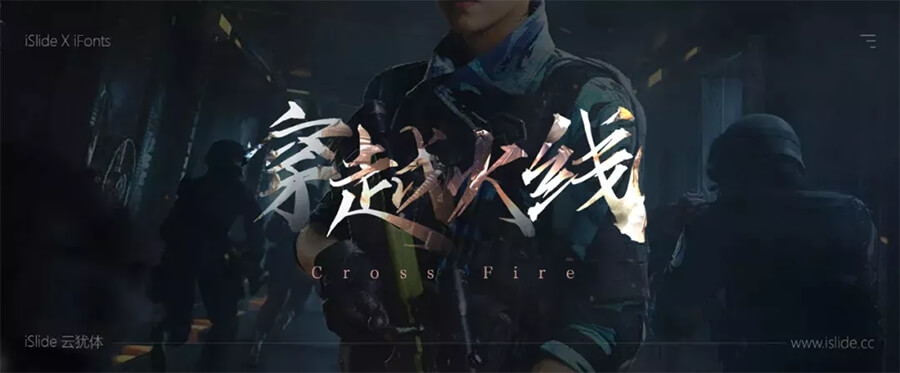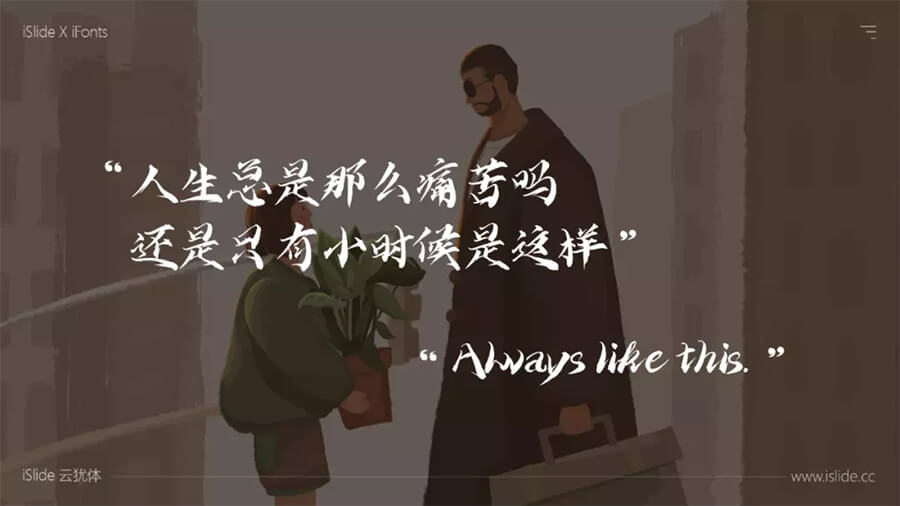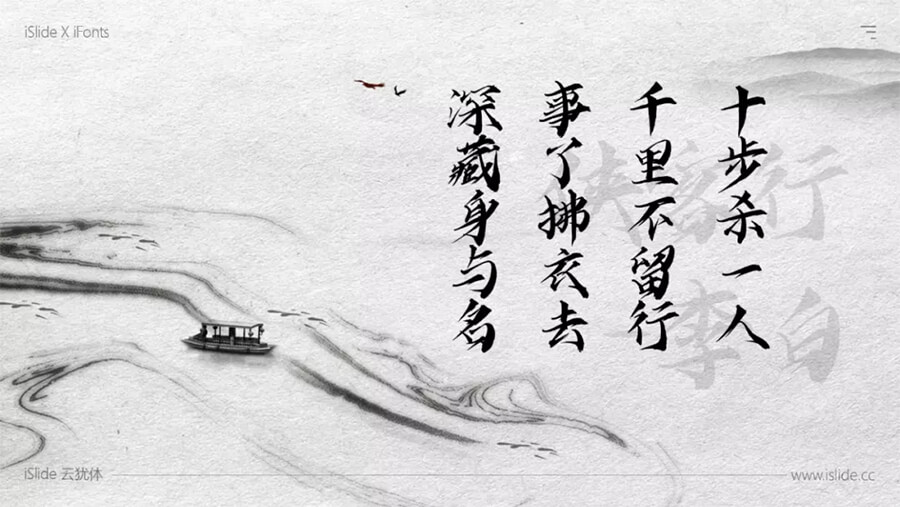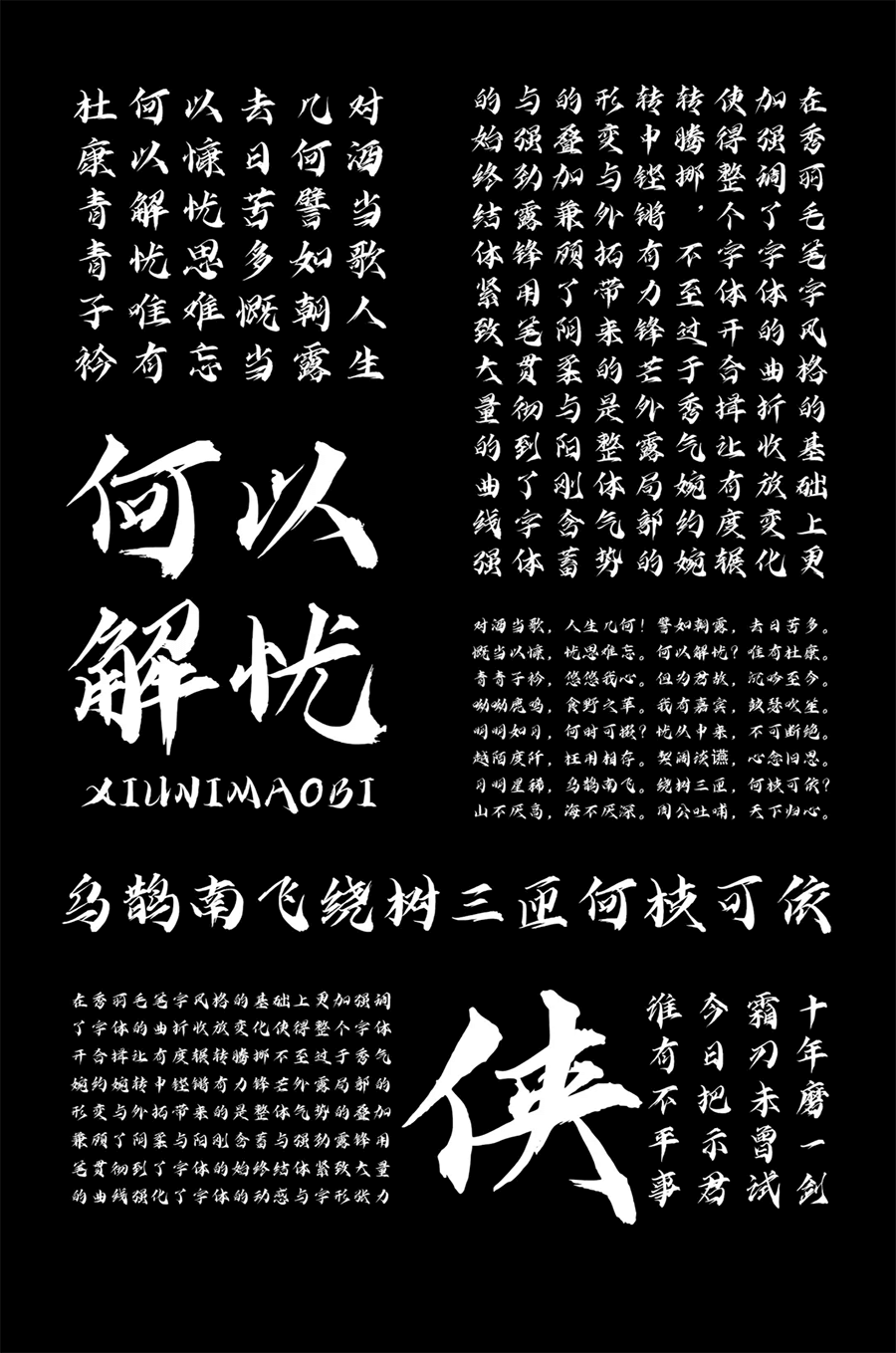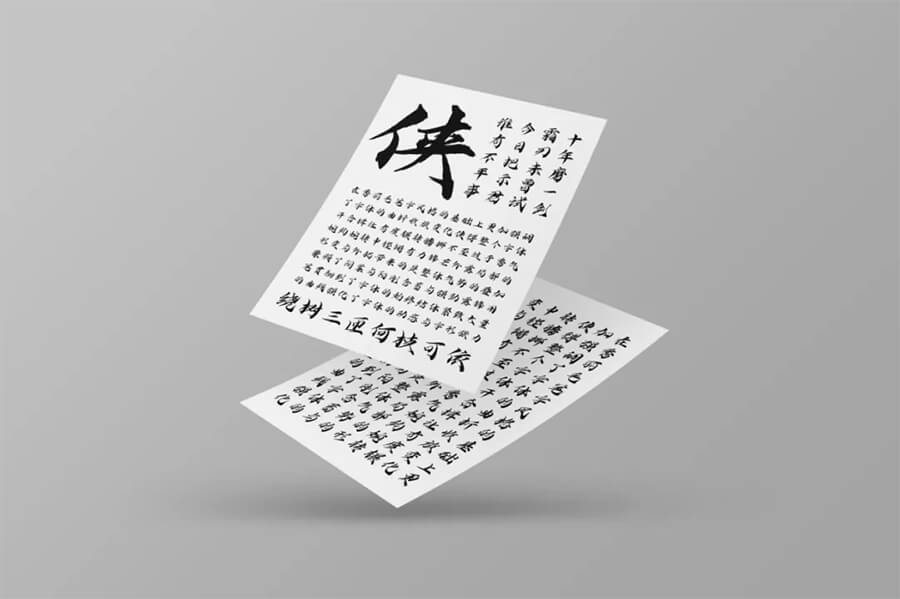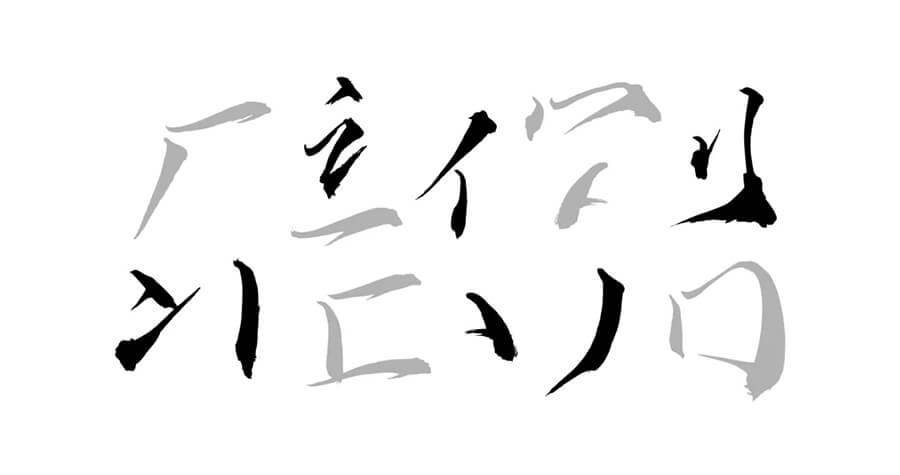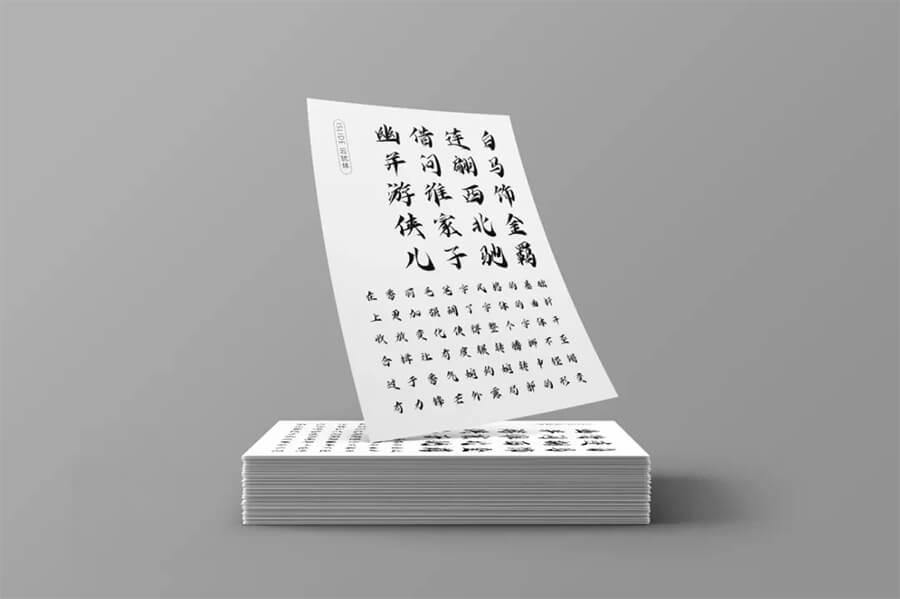
iSlide云犹体:iSlide&iFonts联合推出独家毛笔字体免费商用字体资讯
iSlide云犹体在秀丽毛笔字风格的基础上更加强调了字体的曲折收放变化,使得整个字体开合揖让有度,辗转腾挪,不至过于秀气婉约,婉转中铿锵有力,锋芒外露。
iSlide云犹体局部的形变与外拓带来的是整体气势的叠加,兼顾了阴柔与阳刚、含蓄与强劲。露锋用笔贯彻到了字体的始终,结体紧致,大量的曲线强化了字体的动感与字形张力。
字体应用展示